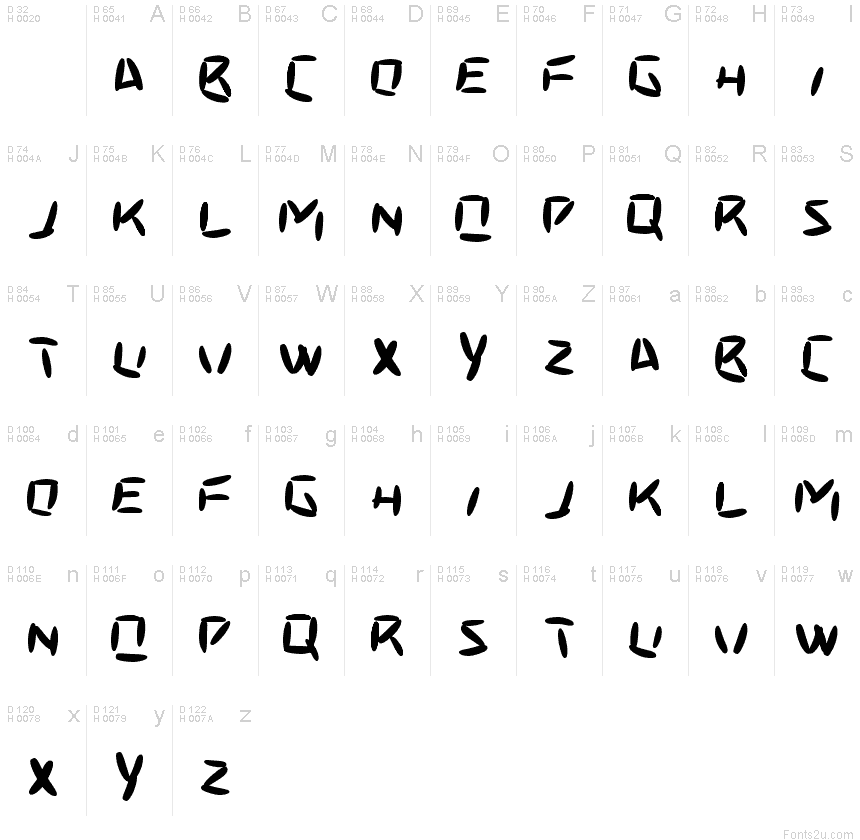
خط Basmati من Temperament Form هو خط مجاني للعناوين بأسلوب القصص المصورة، يتميز بطاقة حيوية وعفوية تشبه الحبر. تبدو الحروف وكأنها خُطّت بسرعة باستخدام قلم تحديد عريض؛ فهي طويلة، مهتزة قليلاً، وغير متساوية بشكل مبهج، مما يضفي على كل كلمة طابعاً يدوياً وتلقائياً. يضفي الإيقاع غير المتكلف في تباعد الحروف وضوحاً في القراءة مع الحفاظ على لمسة "الفوضى" الجذابة.
يضفي استخدام خط Basmati لمسة شخصية تشبه رسومات الكراسات (Sketchbook) على أي تصميم فوراً. إنه مثالي للقصص المصورة، والمجلات المستقلة، وملصقات الأطفال، والمواد التعليمية، ورسوم وسائل التواصل الاجتماعي، والتغليف المرح. هذا الخط المجاني يتألق عند استخدامه بأحجام كبيرة؛ لذا يُفضل تنسيقه مع خط sans serif بسيط للنصوص الثانوية، مما يسمح لطابع Basmati المخطوط بالسيطرة على اللحظات الأكثر تعبيراً وجرأة.